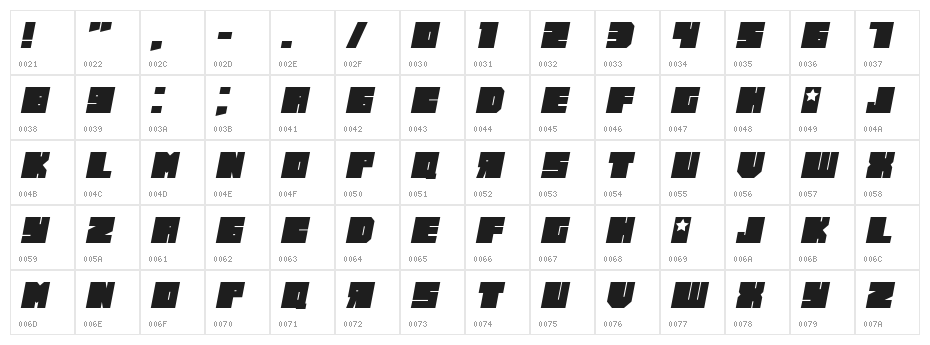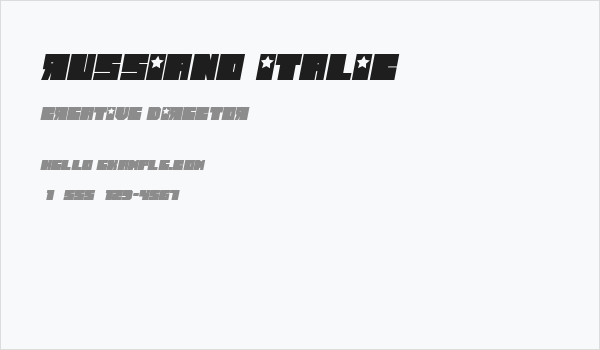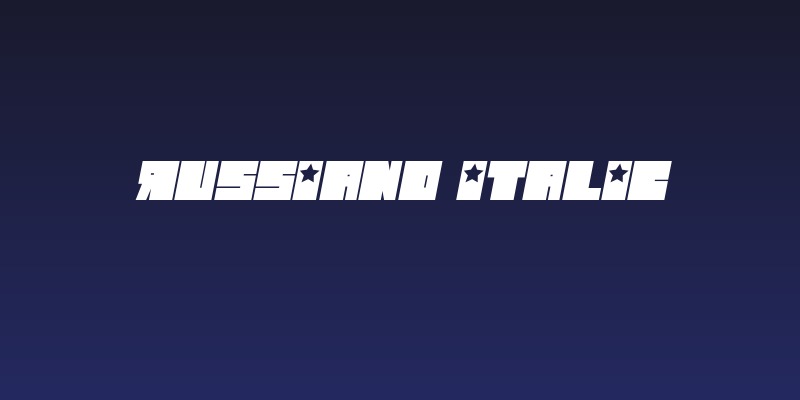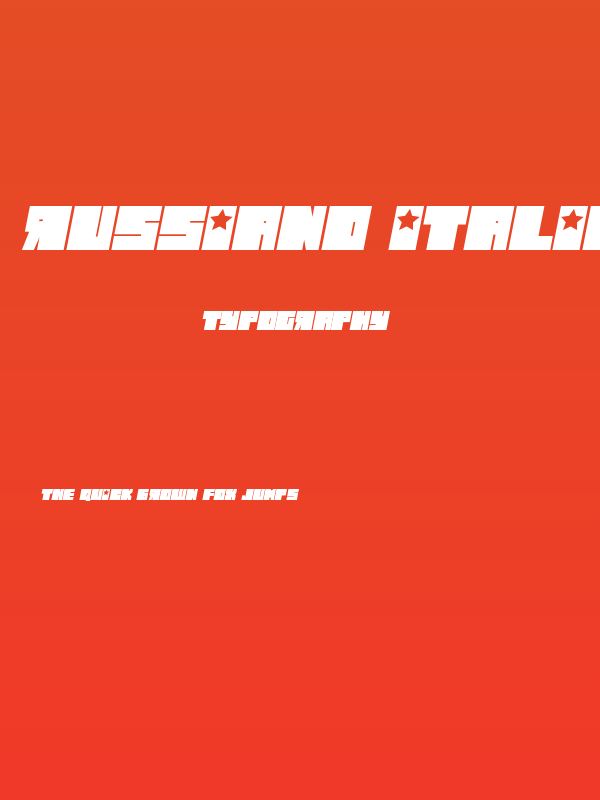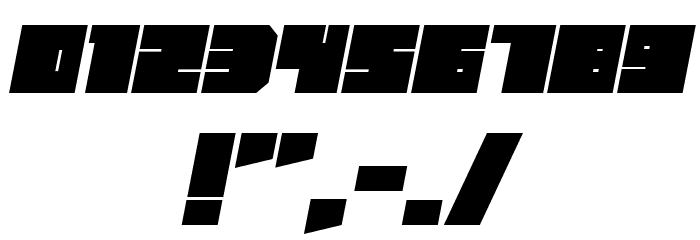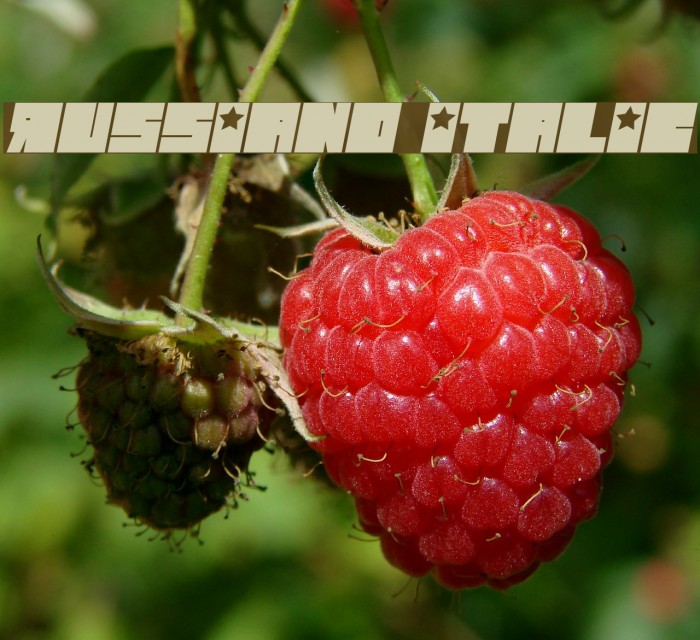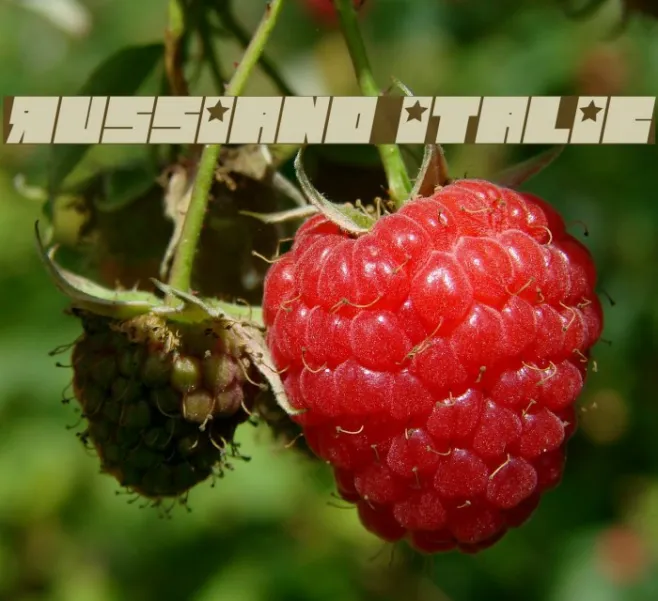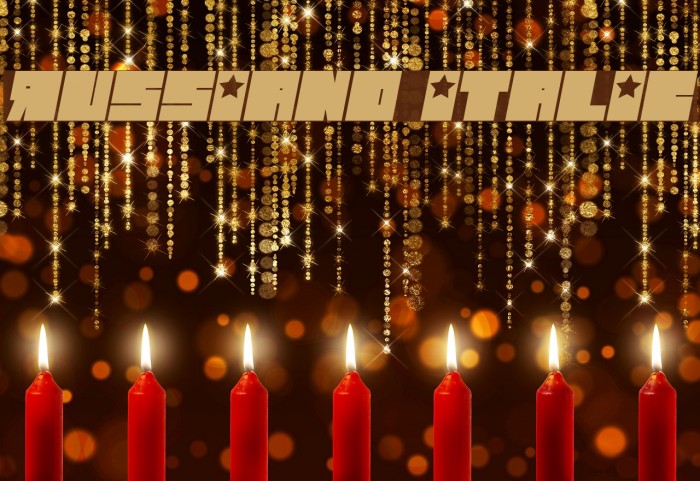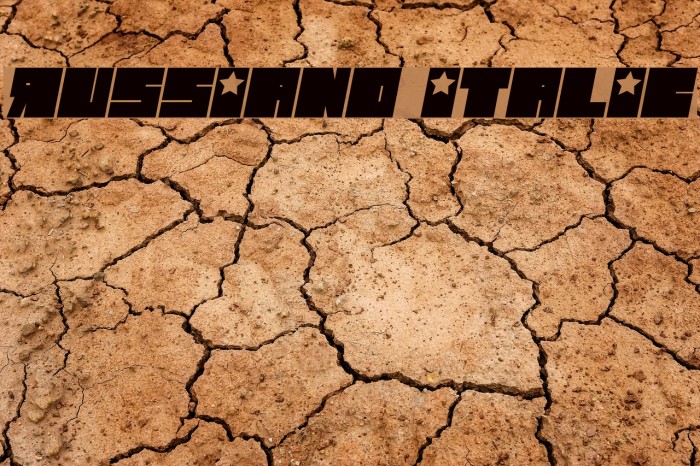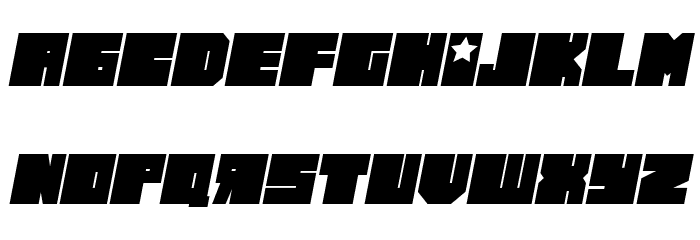
Russiano Italic Font
| Proyectos propuestos | Ideal for use in branding, posters, video game titles, and any project requiring a modern, impactful look. |